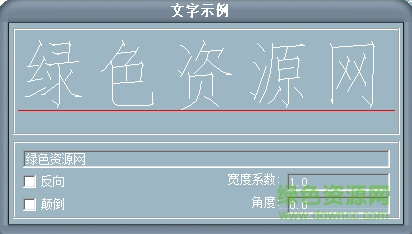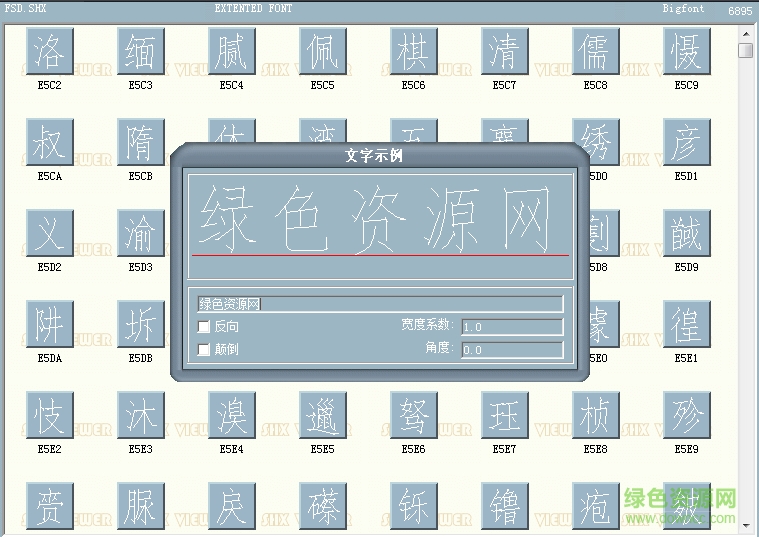
fsdx.shx字體
fsdx.shx字體autocad中必不可少的一款字體,該字體以漢字為主,字體非常的端正大方,并且結(jié)構(gòu)簡潔,筆畫纖細(xì),非常適合用于設(shè)計,感興趣的朋友歡迎下載使用??!
fsdx.shx簡介
fsdx.shx字體是一款非常美觀的cad字體應(yīng)用,以進(jìn)行中文和阿拉伯?dāng)?shù)字的常規(guī)書寫,字體婉約流暢,筆畫纖細(xì),使用起來非常的方便!